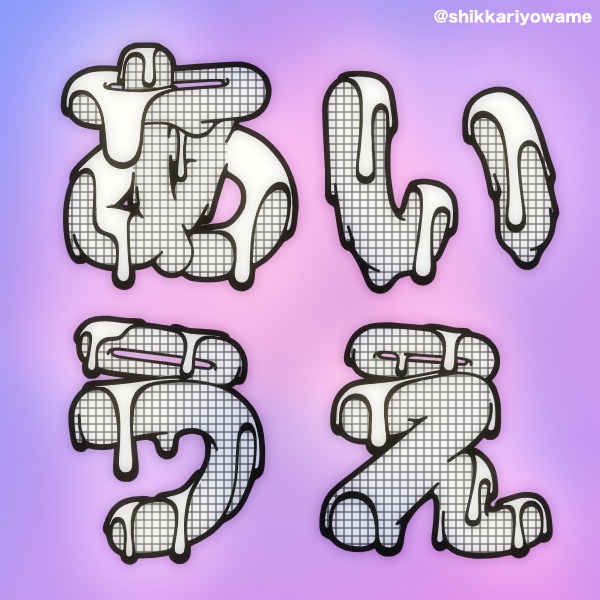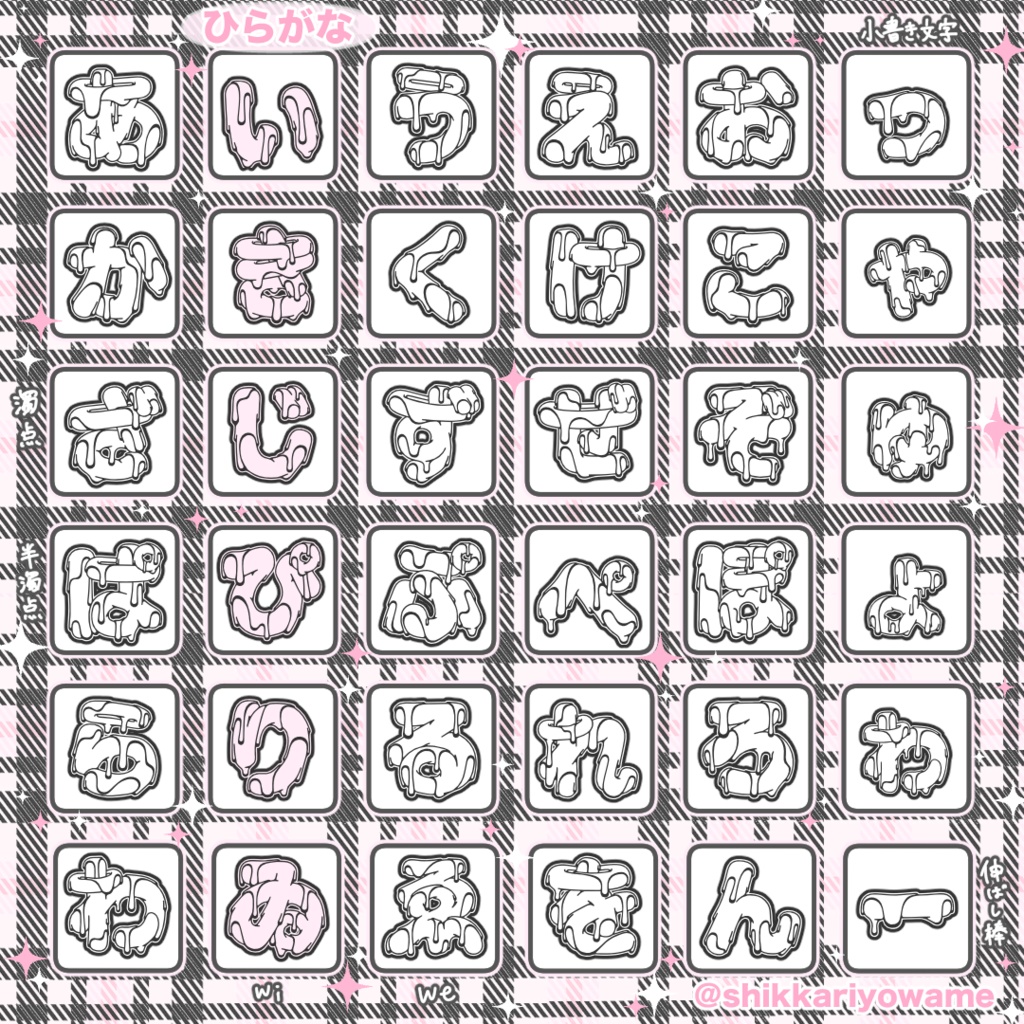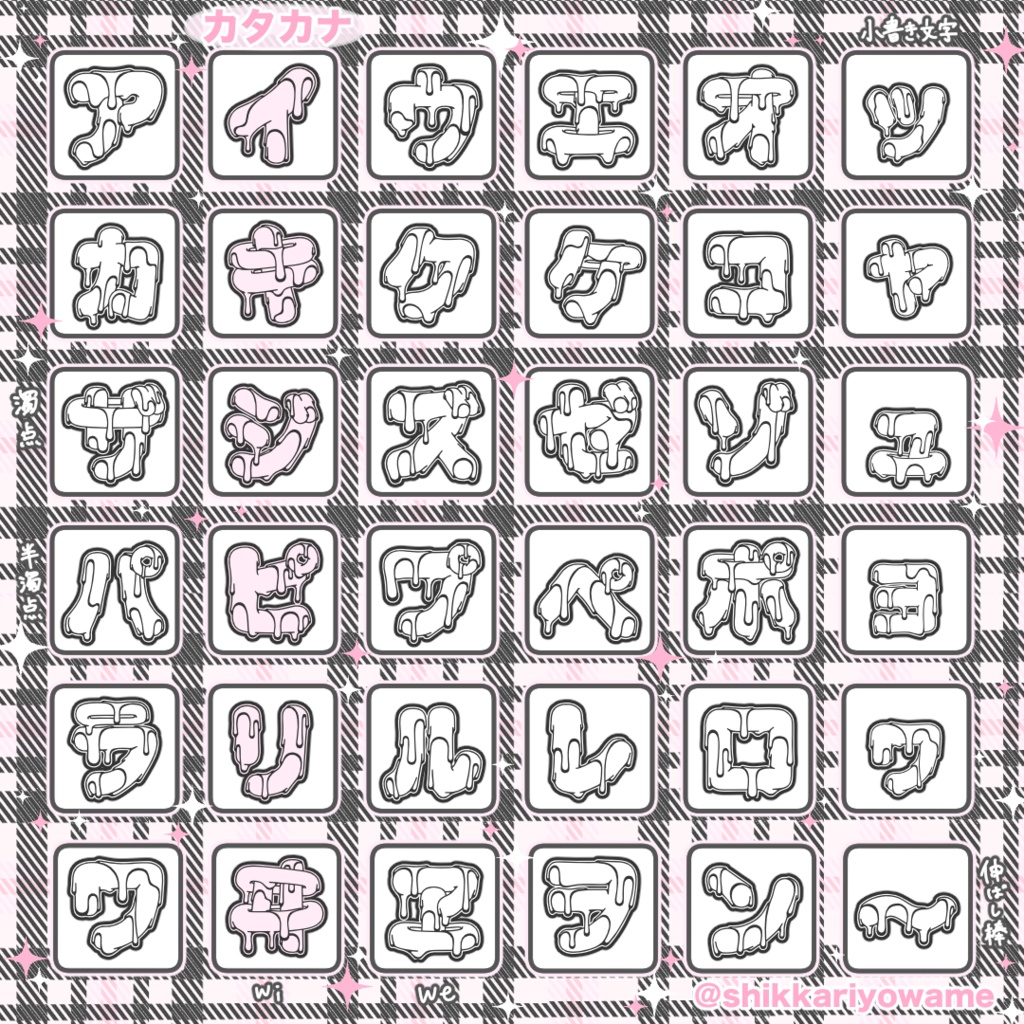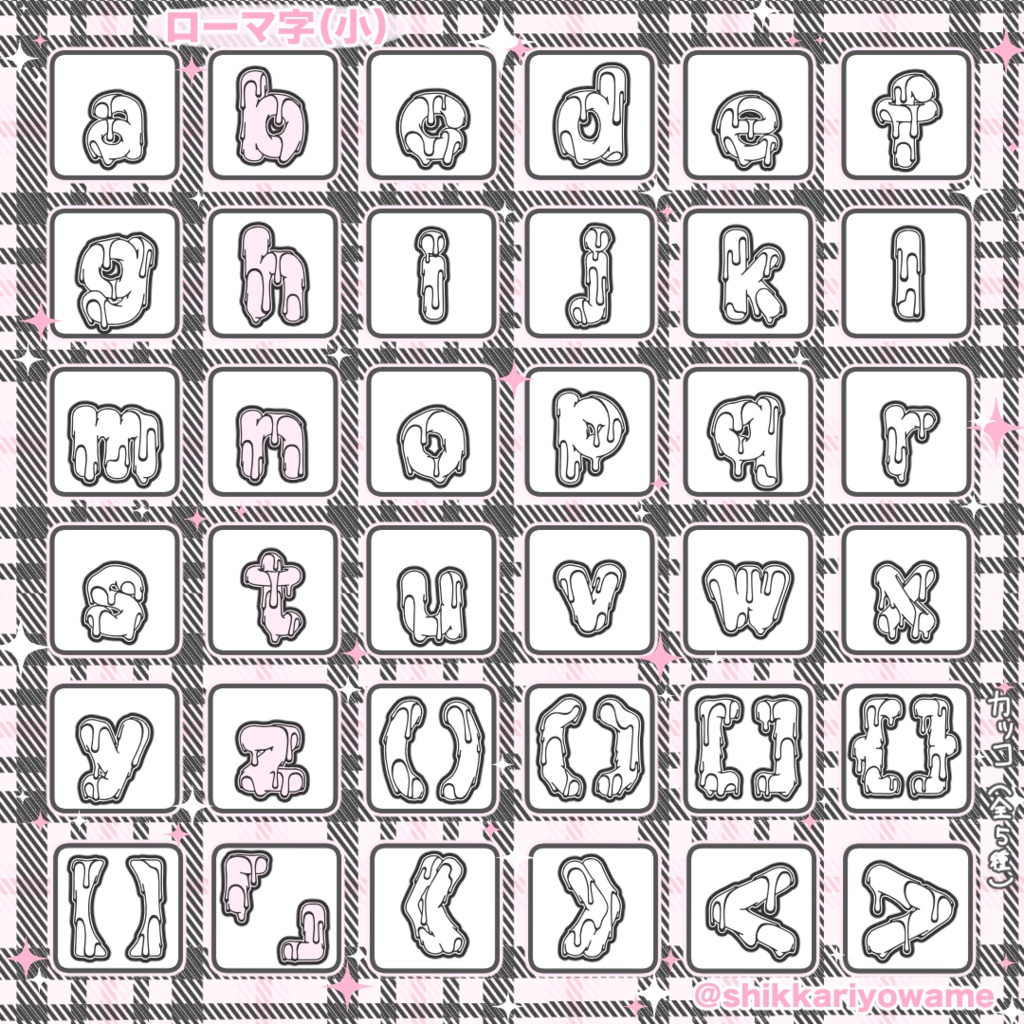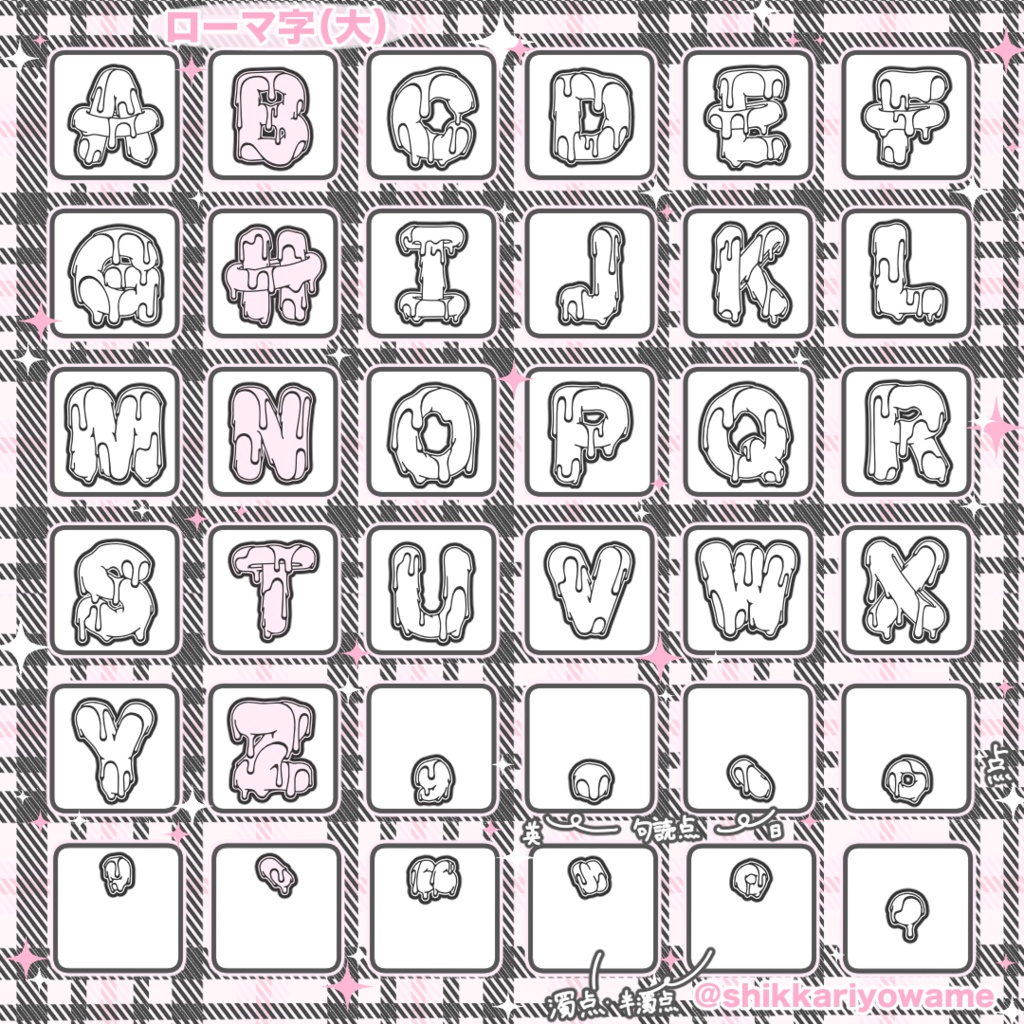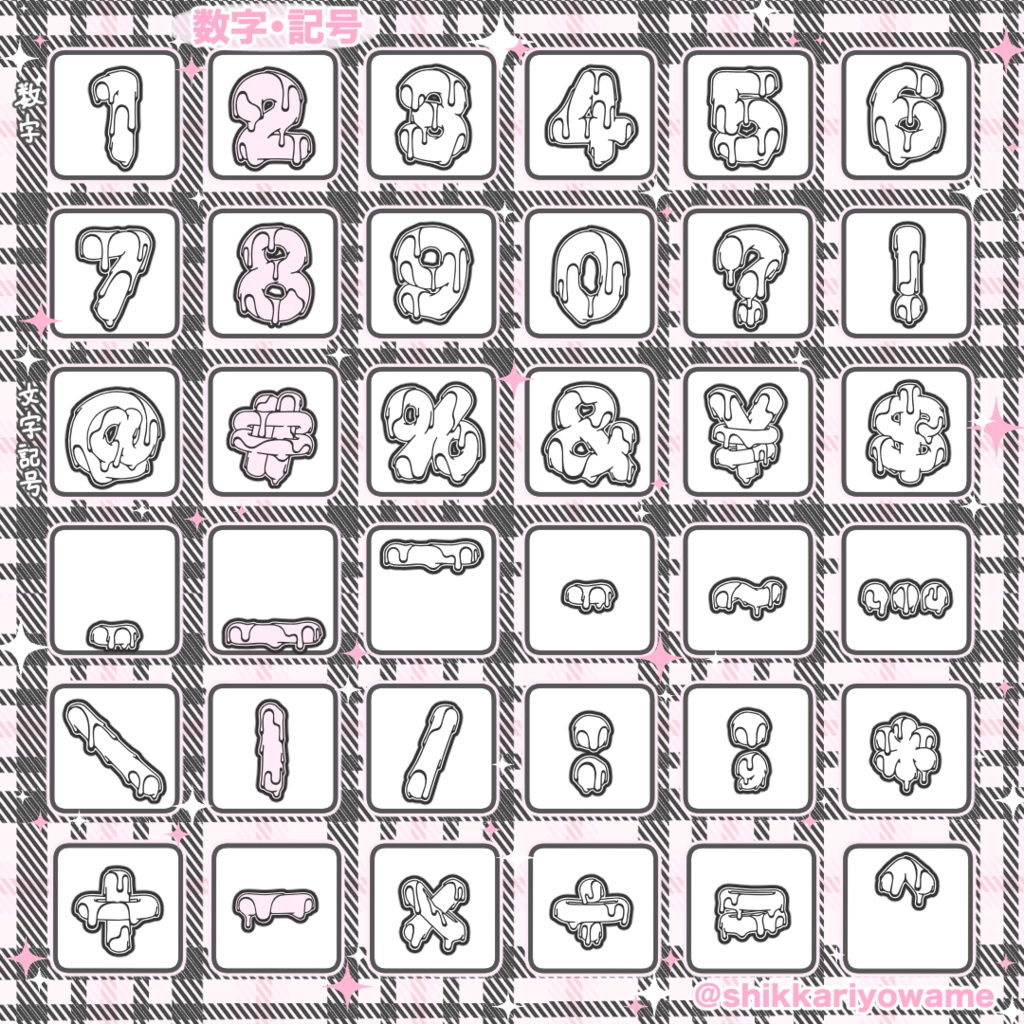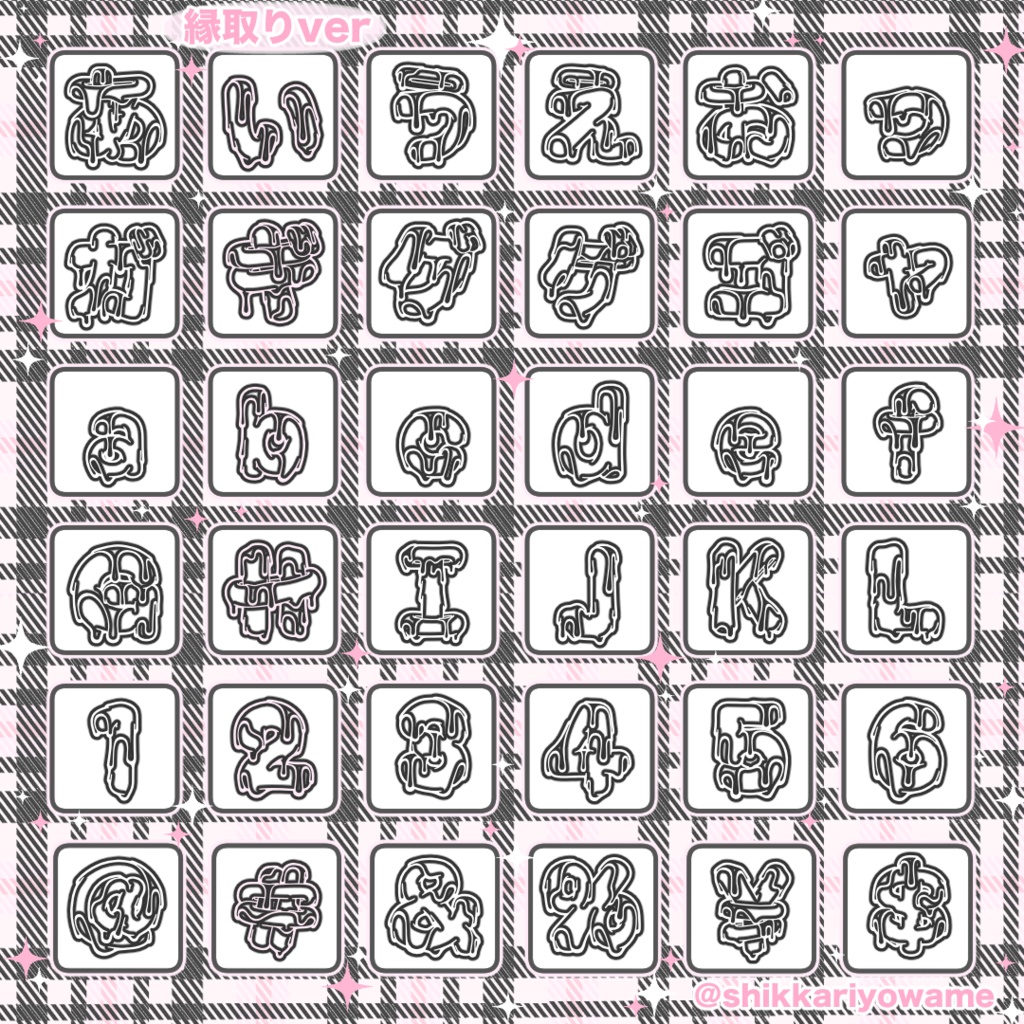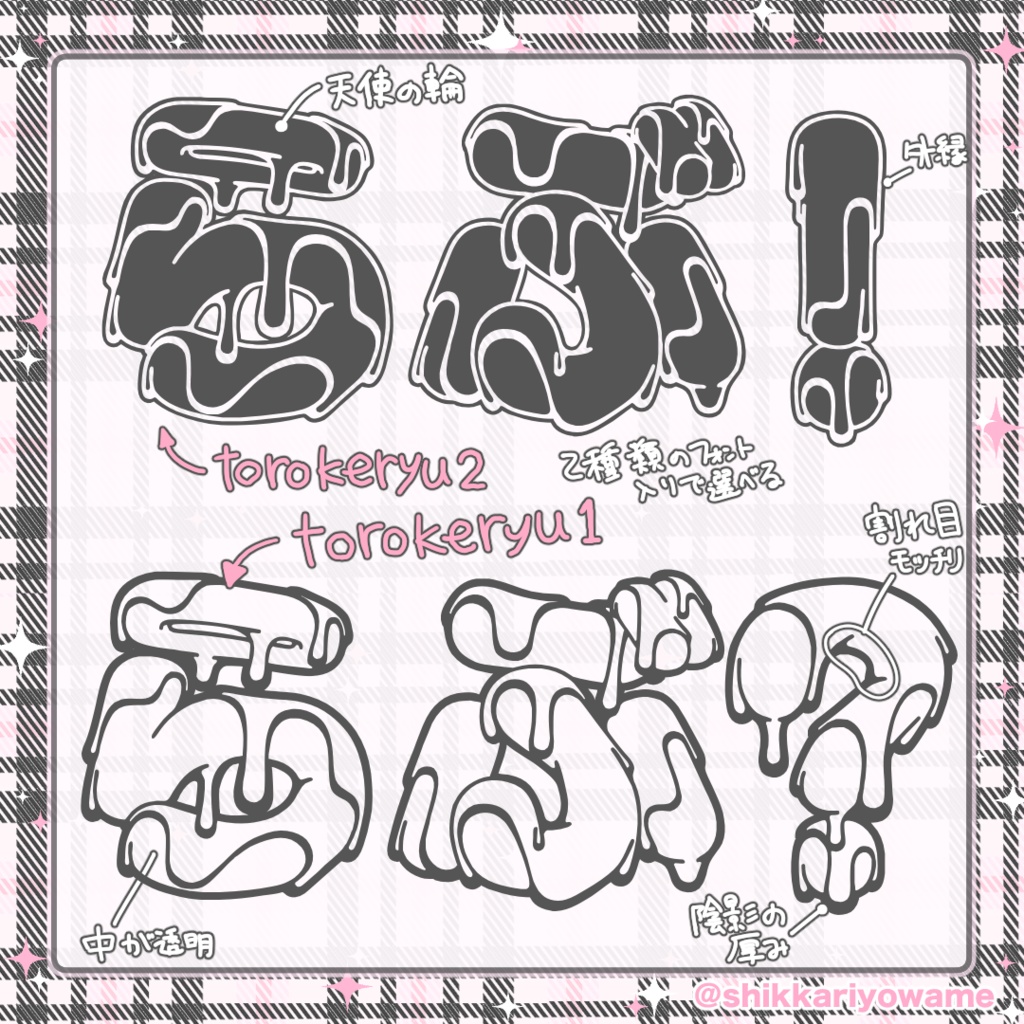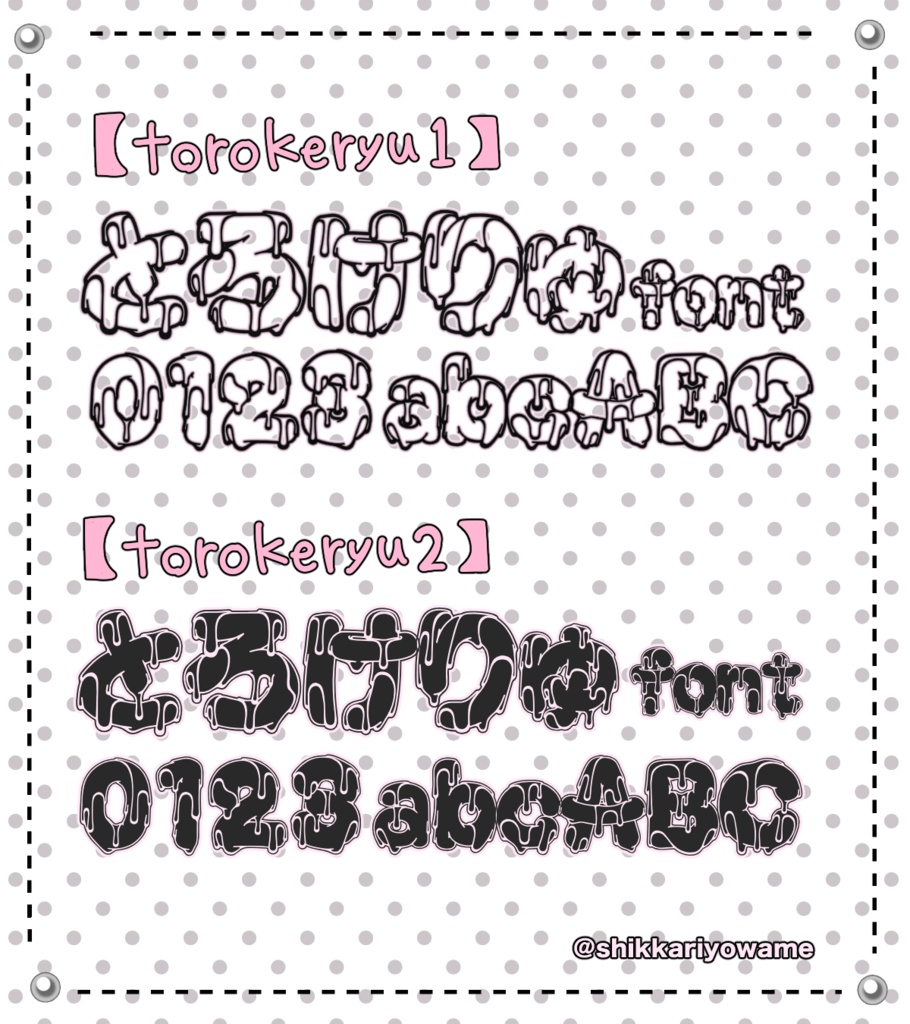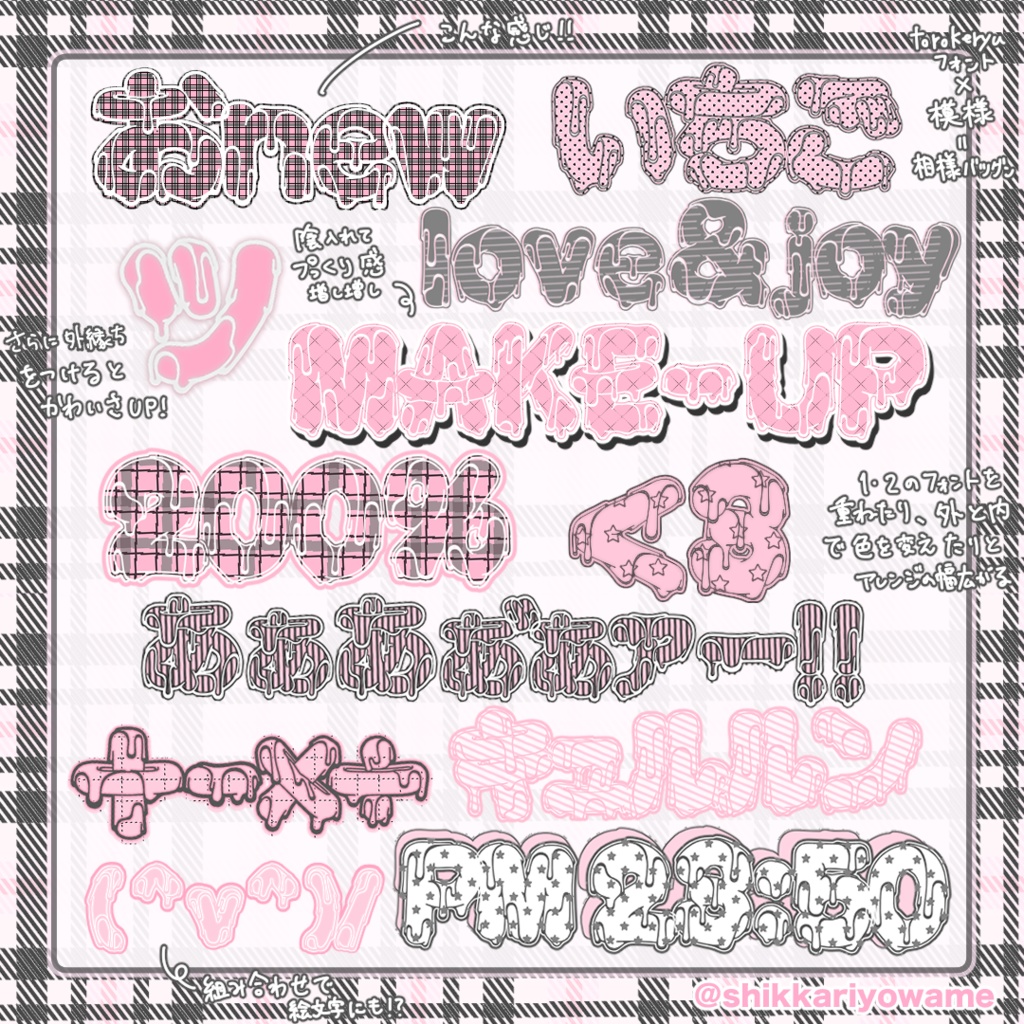
とろけりゅフォント(torokeryufont)【商用可】
『とろけりゅフォント(torokeryufont)』はその名の通り、スイーツが溶けている、垂れている様子をデザインした手書きフォントです。 アイスクリームやプリンのカラメル部分をモチーフにしたので、sweetなコンセプトと相性抜群です。色を変えればスライム風にもなるので見栄えのバリエーション豊かで自分好みにデザインしやすく、非常に使いやすいフォントとなっております。 とろけりゅフォントは、torokeryu1/torokeryu2の2種類のバージョン違いを用意しており、黒塗り部分が違うため自由度が効き、より一層デザインの幅が広く楽しめます。 Xアカウント( https://x.com/shikkariyowame2 )をフォローでどなたでもDL可 【無料版について】 無料版は完全try out 形式となっております。torokeryu1の数字のみの収録なので試し打ち感覚でご利用ください。 【収録内容】 ・torokeryu1/torokeryu2(2つのバージョン違い同梱入り) ・TTFフォント ・ひらがな、カタカナ、数字、記号、アルファベット ・利用規約 【利用規約】 商用利用可能です。 (ご依頼での使用、ロゴ、映像、電子書籍、ゲーム、成人向け作品での使用、変形・加工も可能) 著作権は放棄しておりません。 フォントファイルの無断再配布、販売、譲渡、商標登録は禁止です。 (商標登録は加工した画像は可) 当フォントの使用に関連して生じたいかなる損害、トラブルは作者は責任を負いません。自身の責任でご使用ください。 詳細はフォントファイルと一緒に規約テキストを同梱しておりますので、そちらからご確認お願いします。 (※https://lit.link/shikkariyowameからもご確認いただけます) ※フォント更新 2026/03/22 幅感調整、フォント名を日本語表記(v2)